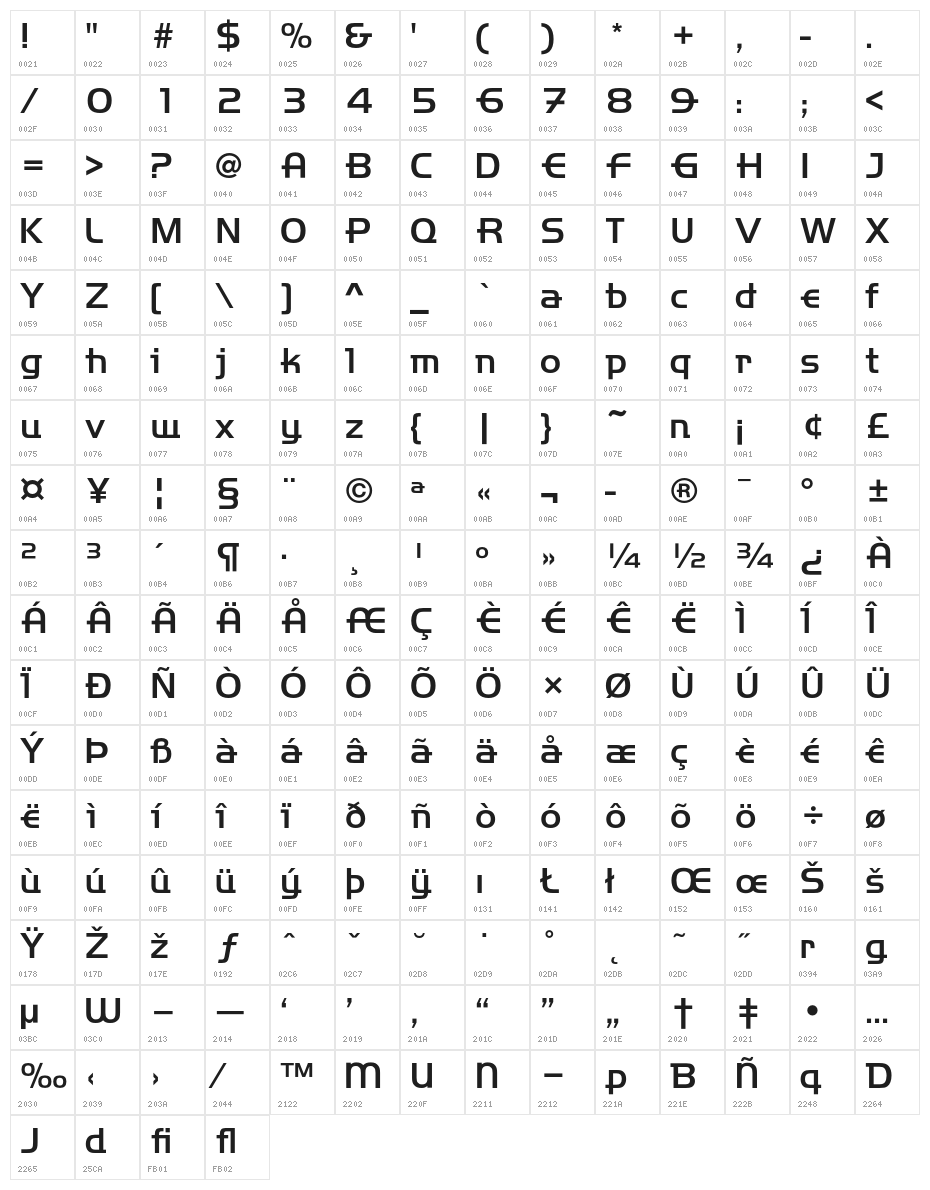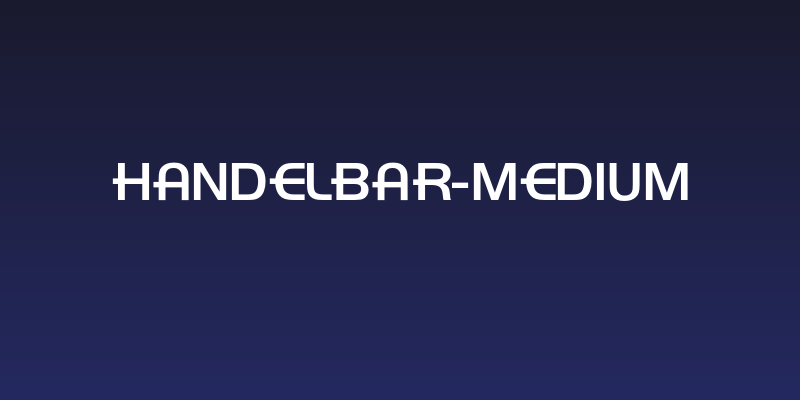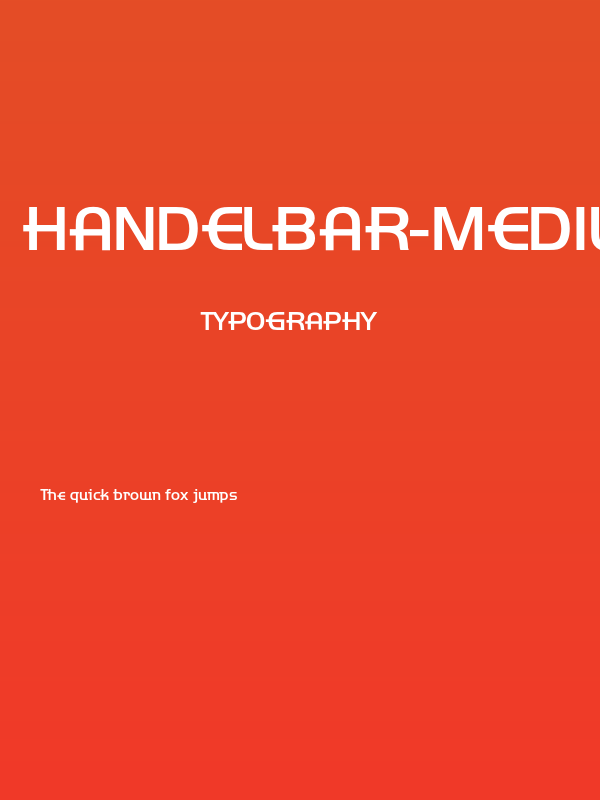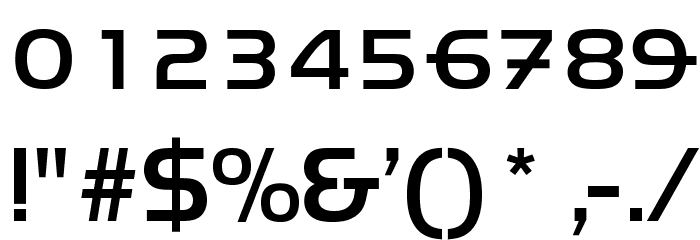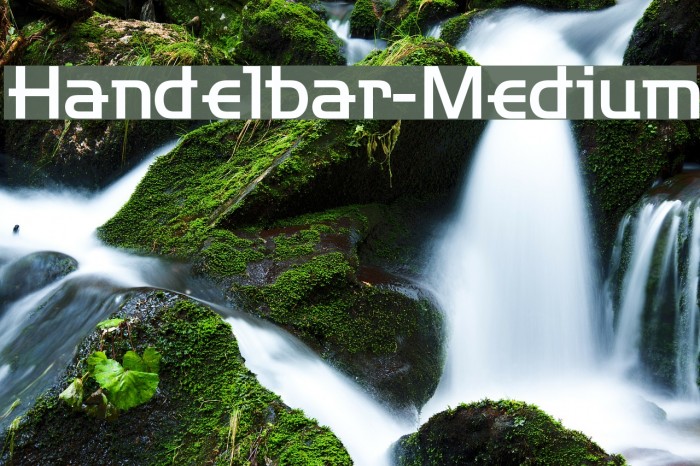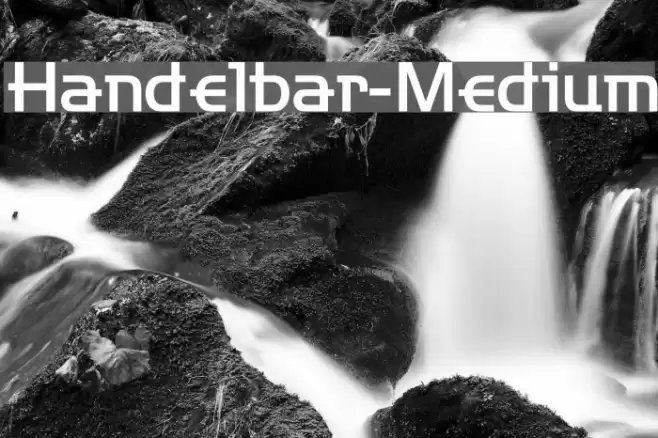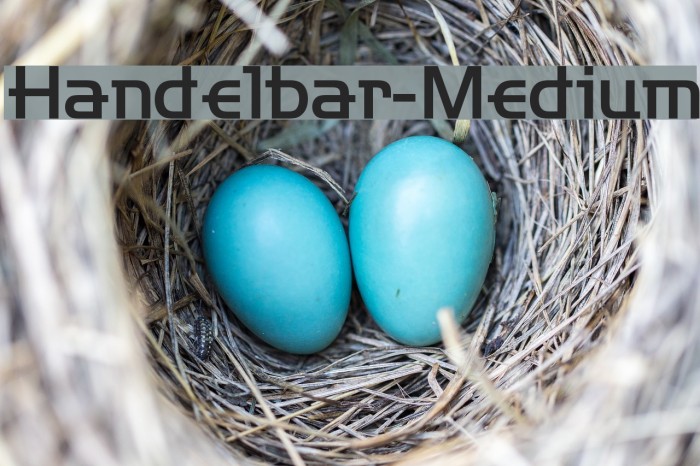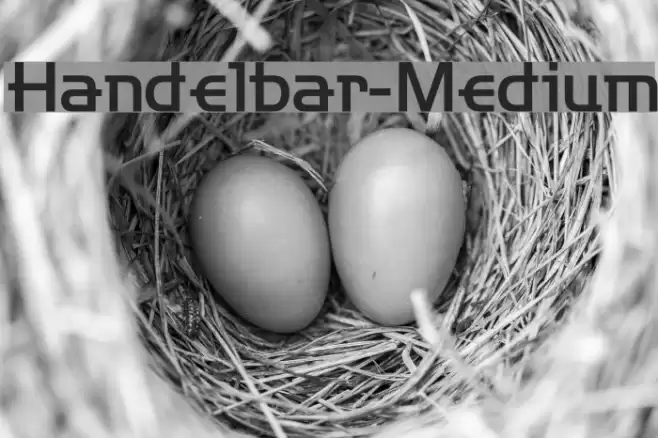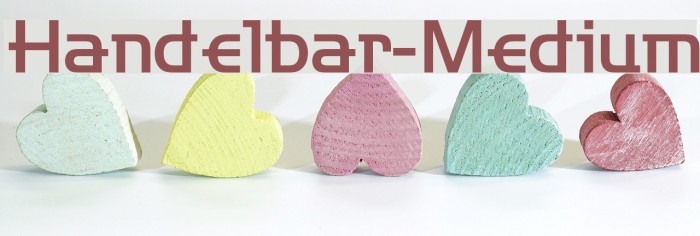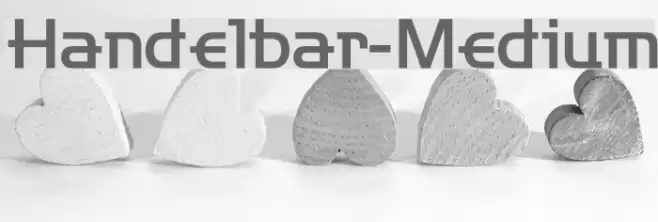
Handelbar-Medium Font
| ウェイト | Medium |
| 用途 | Headlines, Logos, Digital interfaces |
| おすすめプロジェクト | Ideal for technology branding, modern advertising, futuristic posters, and digital interfaces. |